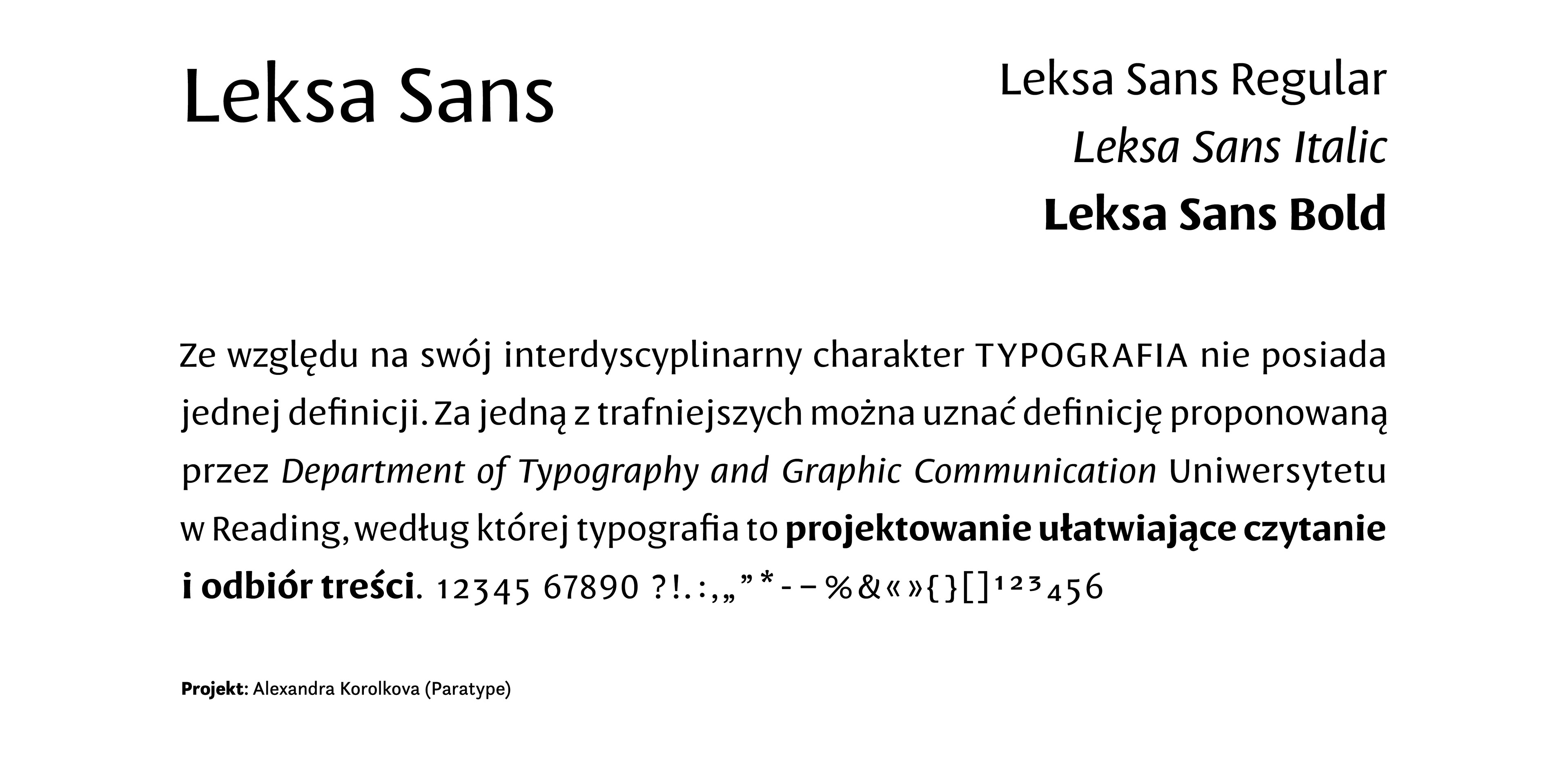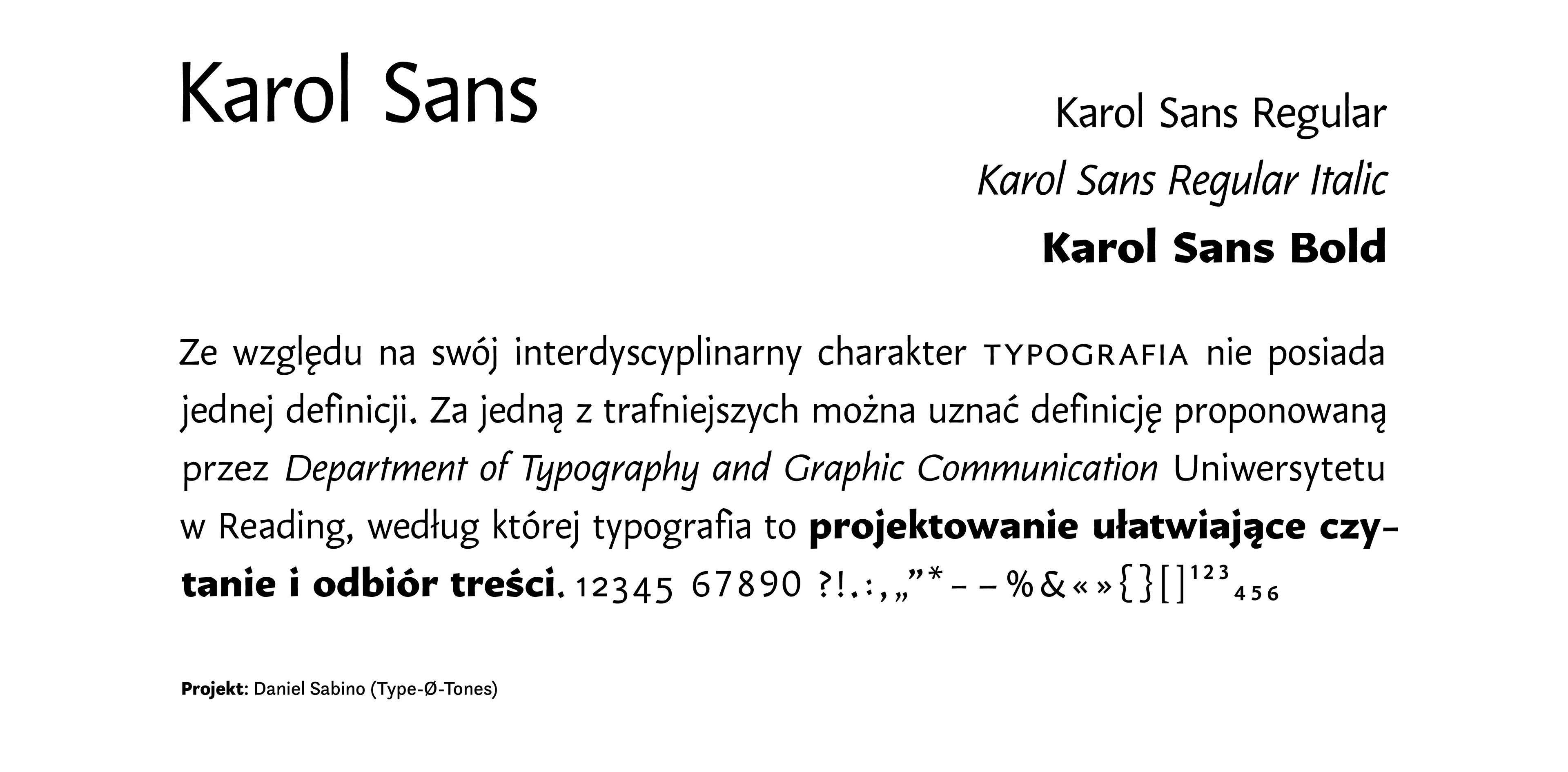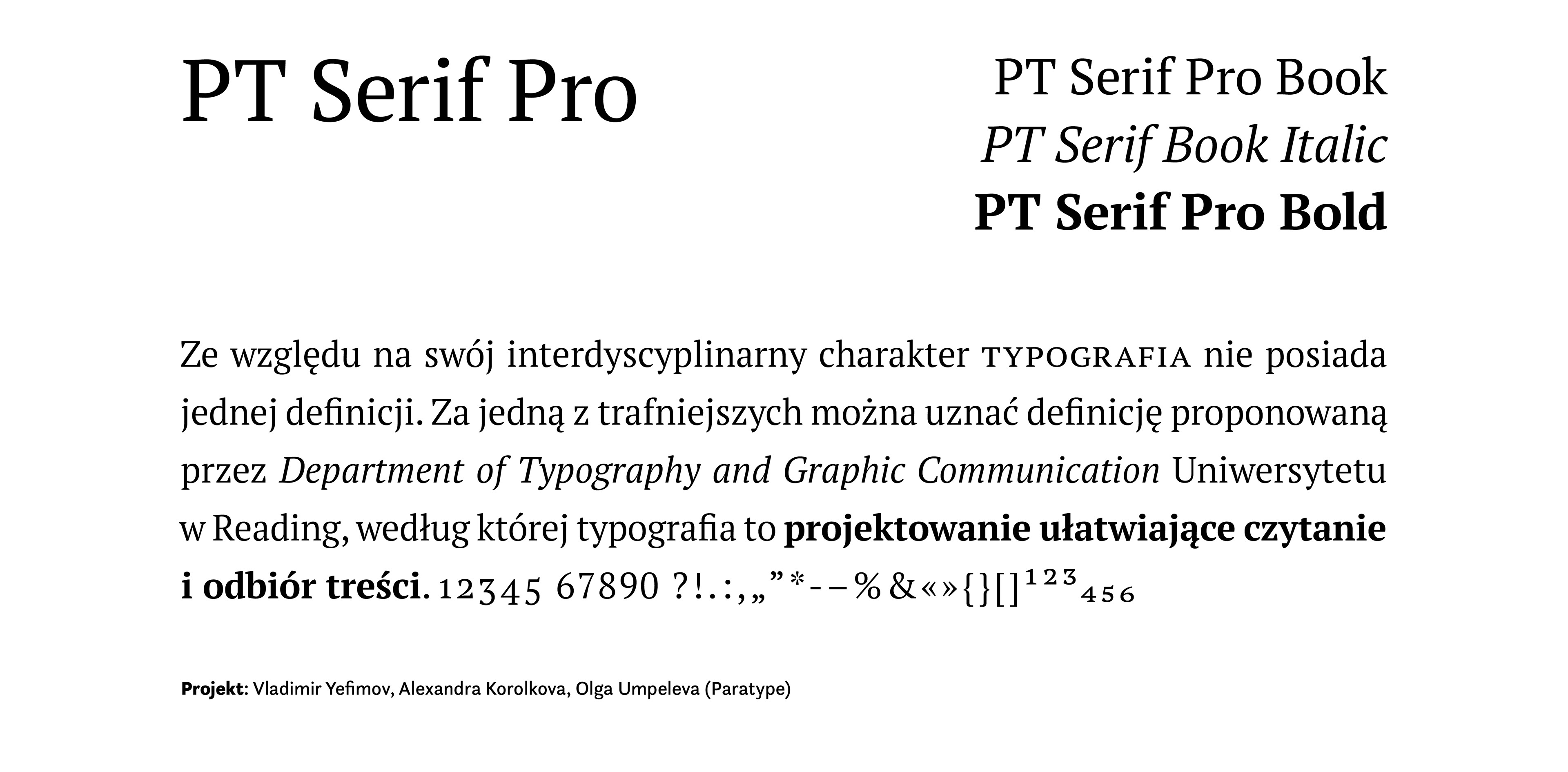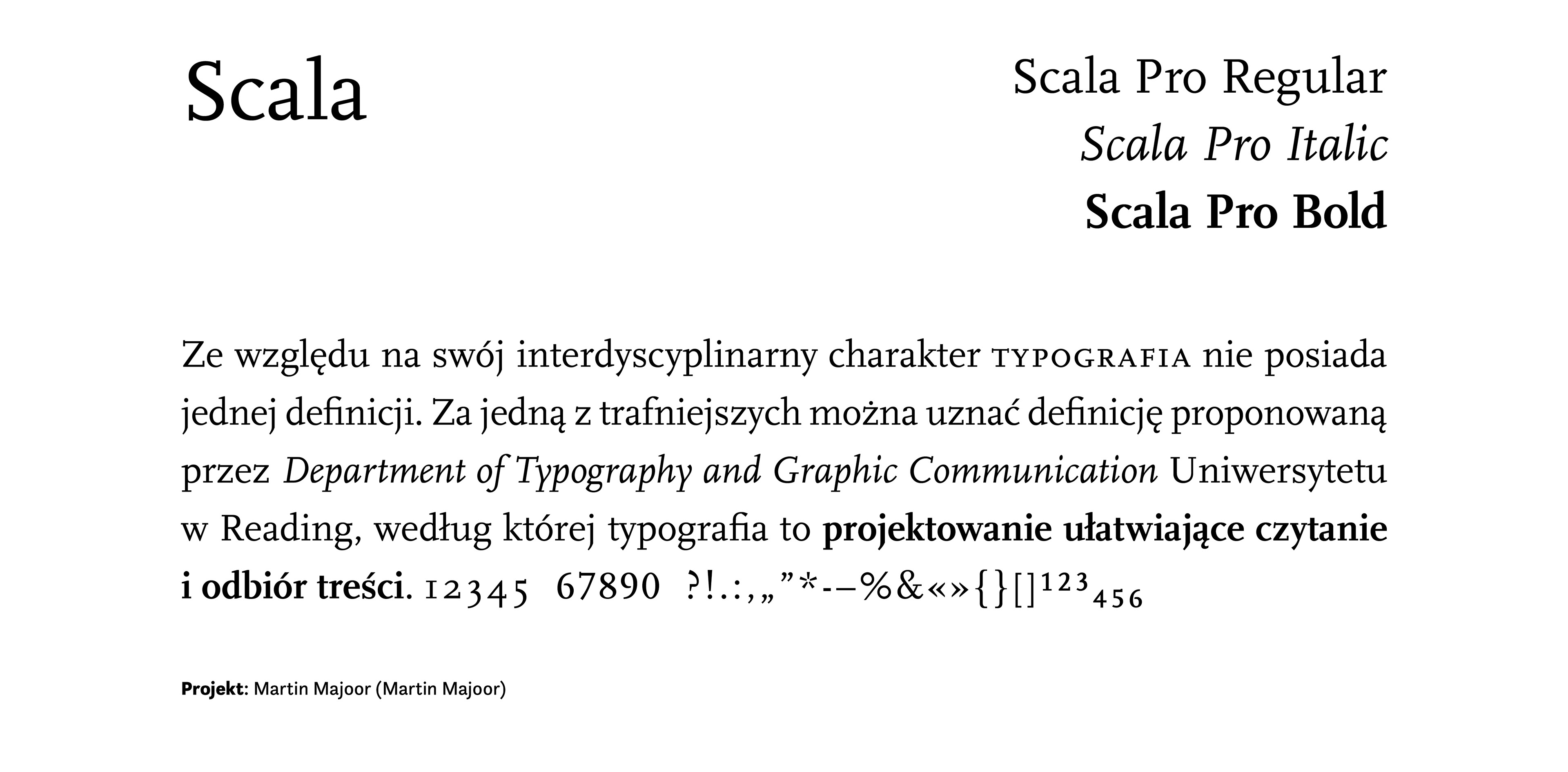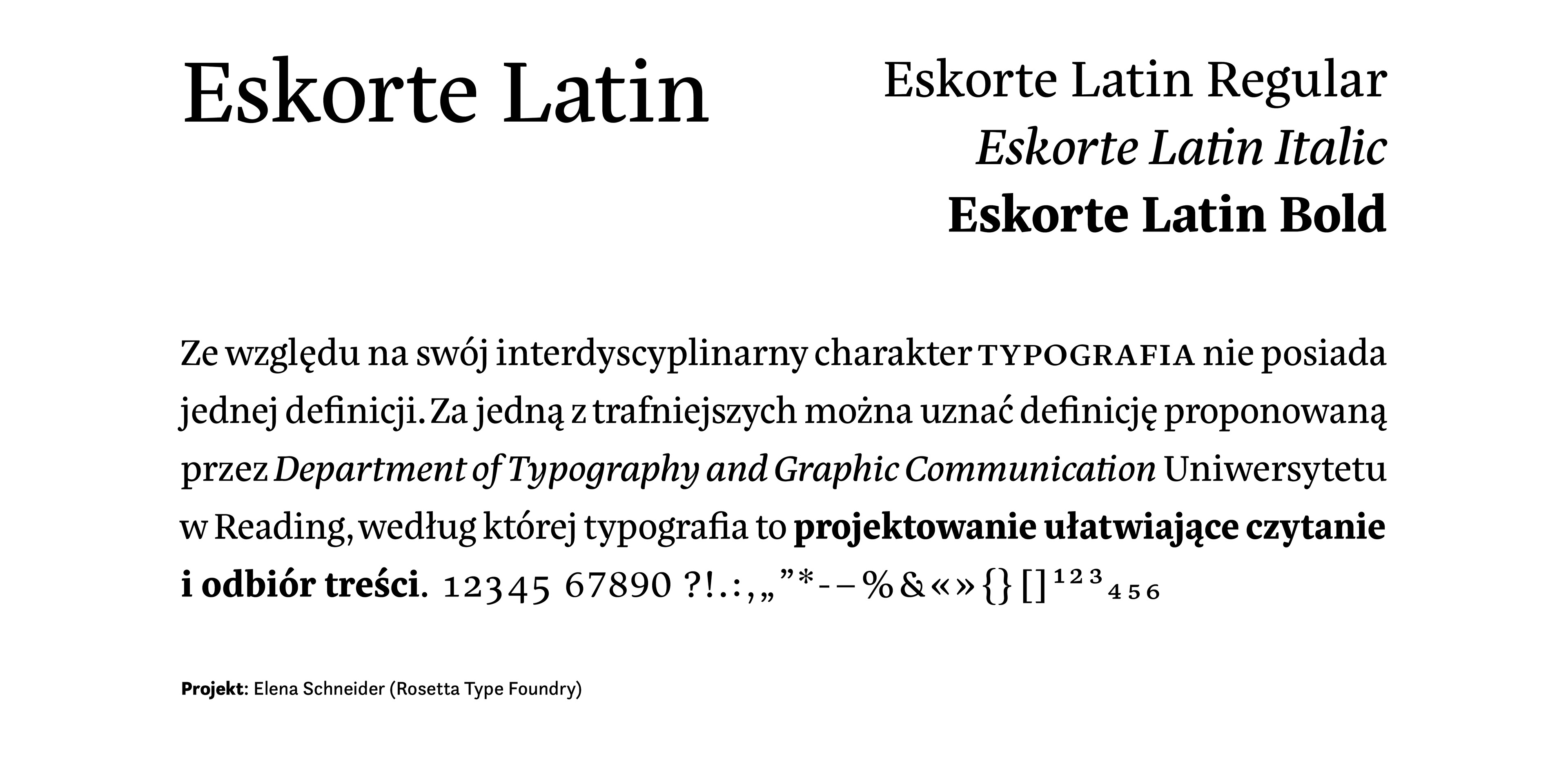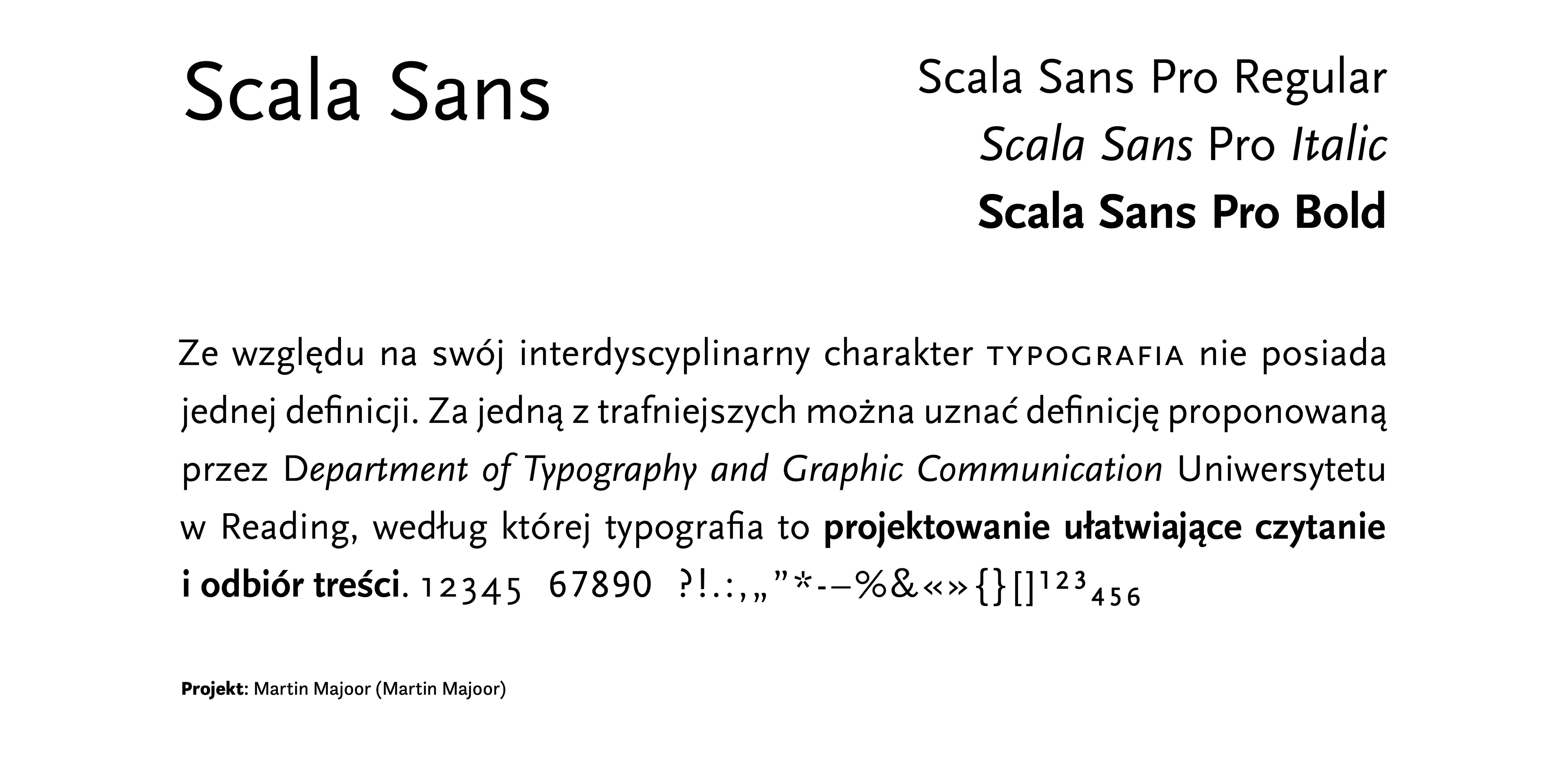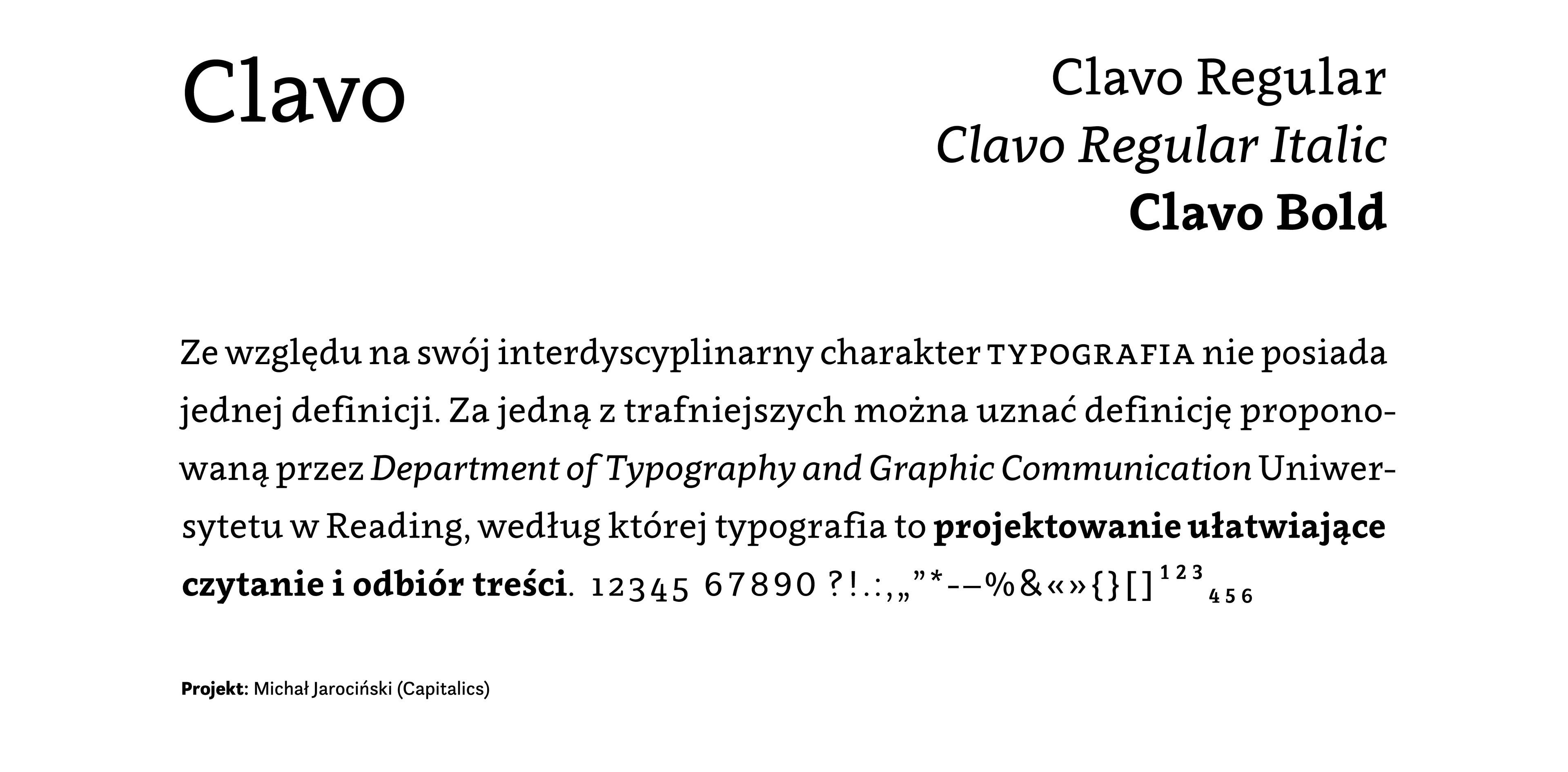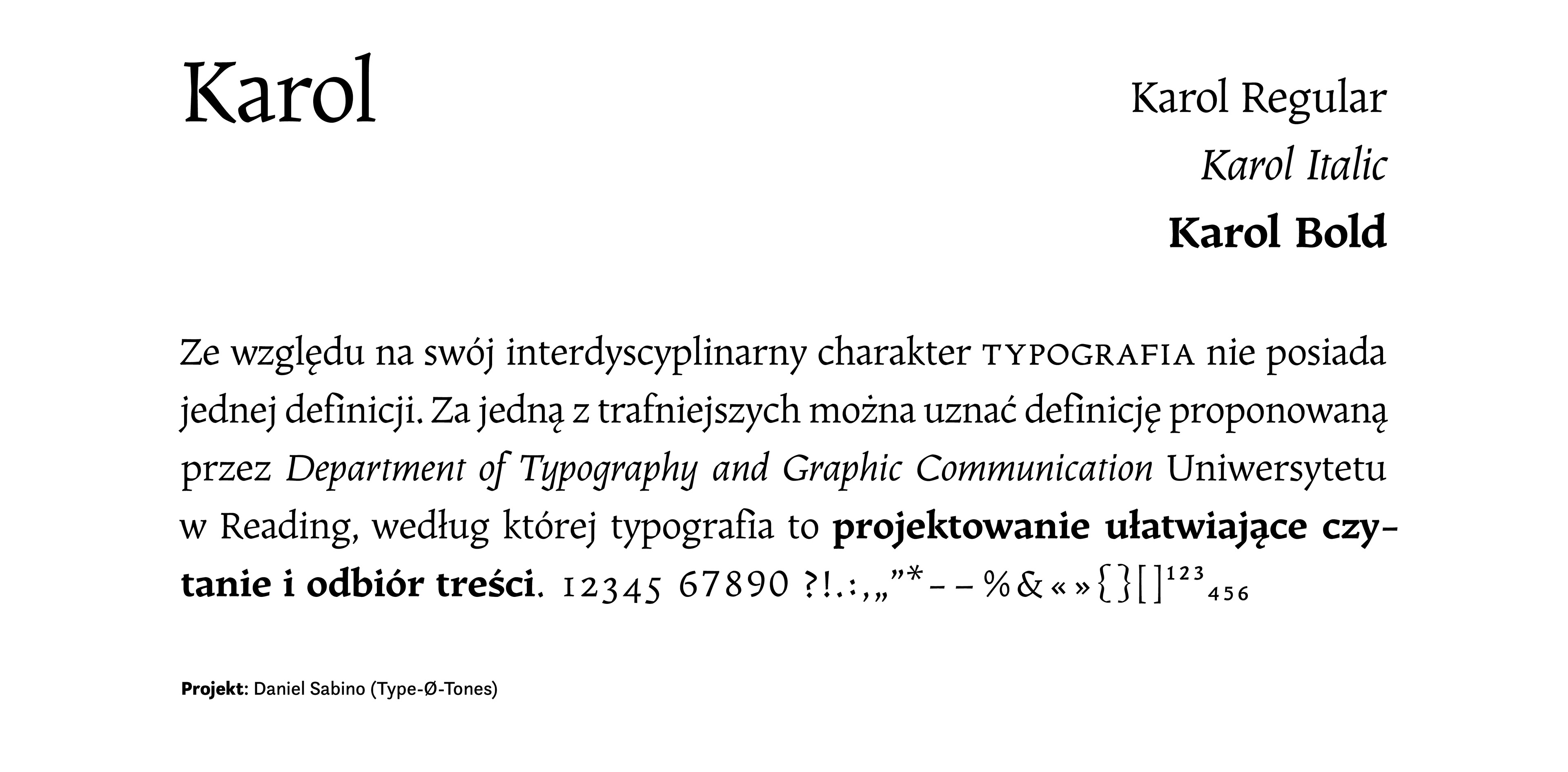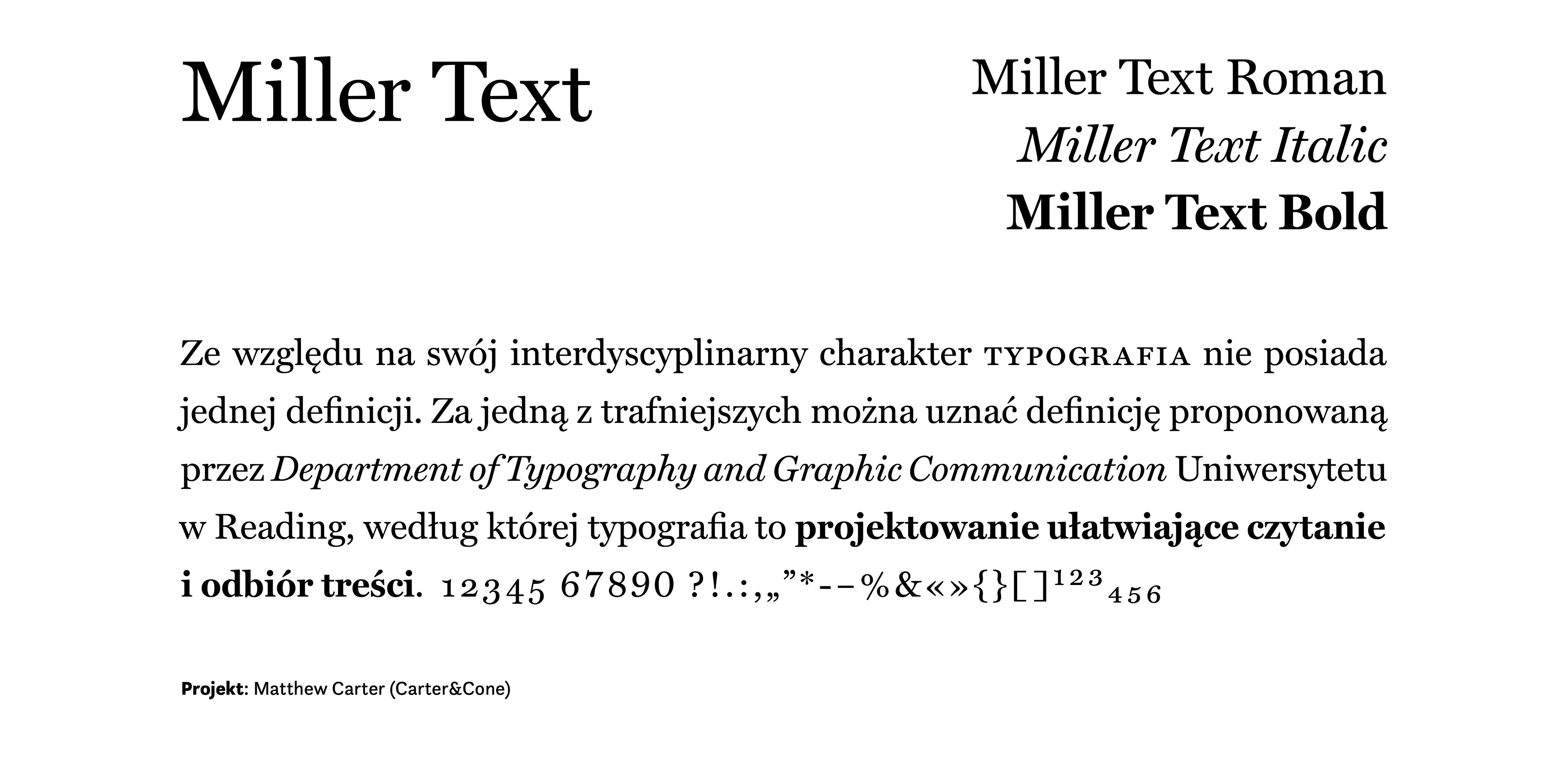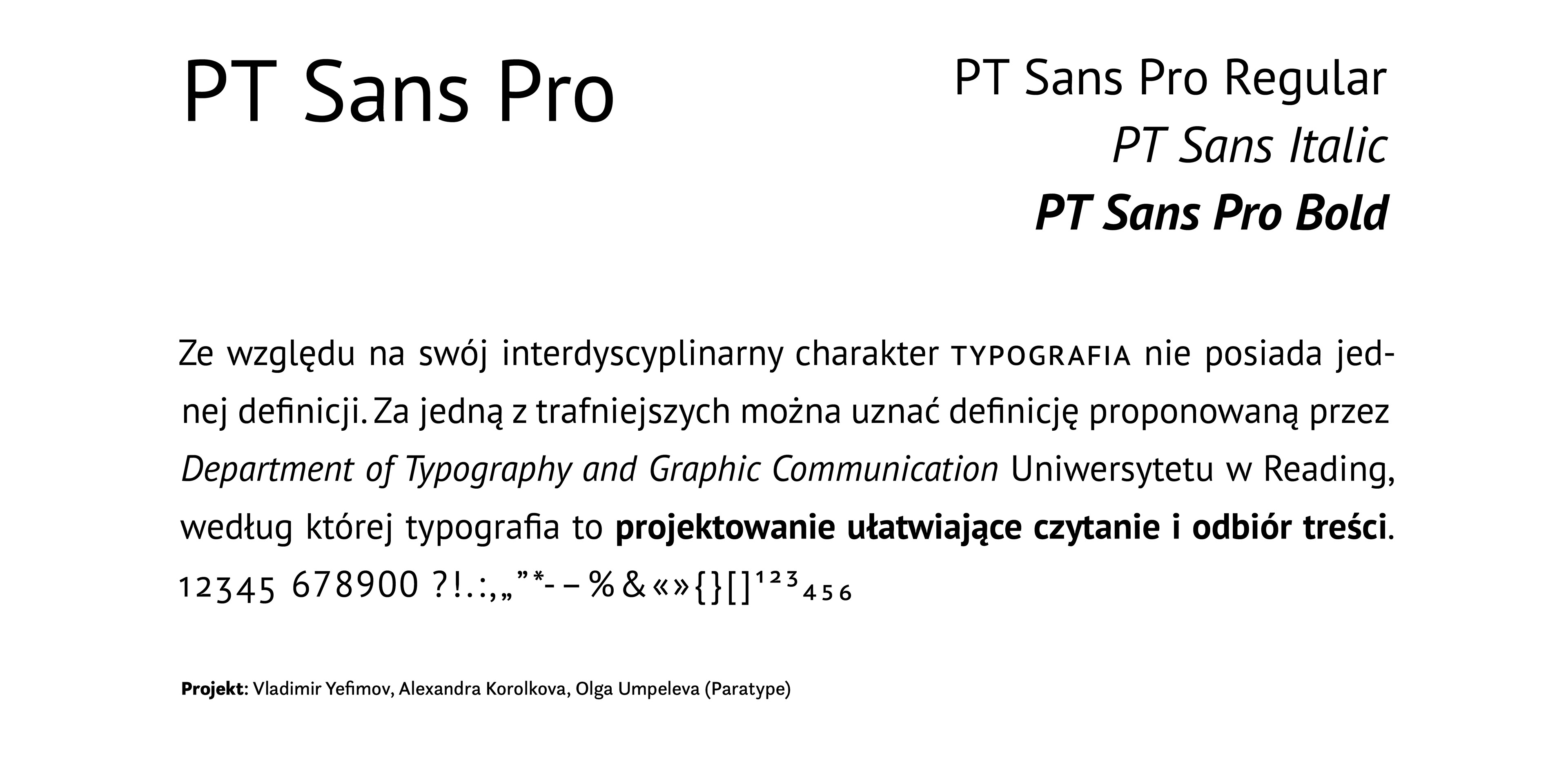
Kroje dziełowe w kolekcji
Cel artykułu
Przystępując do projektu, w którym musimy opracować dużą ilość tekstu (książki, katalogi, magazyny, gazety), zawsze stajemy przed wyzwaniem dotyczącym wyboru odpowiedniego kroju pisma.
Doświadczeni projektanci doskonale wiedzą, że przeglądanie rozbudowanych bibliotek fontów to wymagające i czasochłonne zadanie. Zazwyczaj proces ten obejmuje pobieranie, testowanie oraz analizę dostępnych w foncie glifów. Artykuł ten powstał z myślą o tym, aby uprościć to zadanie.
Przygotowany zestaw zawiera starannie wyselekcjonowane kroje dziełowe (ang. paragraph, text typefaces), stworzone przez uznanych projektantów i wydane przez renomowane domy typograficzne. Wszystkie prezentowane fonty są dostępne na platformie Adobe Fonts w ramach abonamentu Adobe Creative Cloud.
Próbki tekstu oraz tabela
Poniższe ilustracje prezentują próbki tekstu, które pozwalają na szybą ocenę wyglądu i charakteru poszczególnych krojów pisma.
Kryteria wyboru
1. Wysoka czytelność znaków (ang. legibility)
2. Obecność polskich znaków diakrytycznych
3. Występowanie kursywy oraz co najmniej jednej odmiany pogrubionej – umożliwiających wyróżnianie fragmentów tekstu oraz projektowanie tytułów i śródtytułów.
4. Dostępność rozbudowanych funkcji zecerskich (ang. OpenType features), przydatnych w składzie bardziej wymagających publikacji. Do najważniejszych należą: kapitaliki (ang. small caps), cyfry nautyczne (ang. oldstyle figures) i cyfry wersalikowe (ang. lining figures) w wersjach proporcjonalnych (ang. proportional) i tabelarycznych (ang. tabular), oraz cyfry w indeksie górnym (ang. superscript) – stosowane w przypisach.